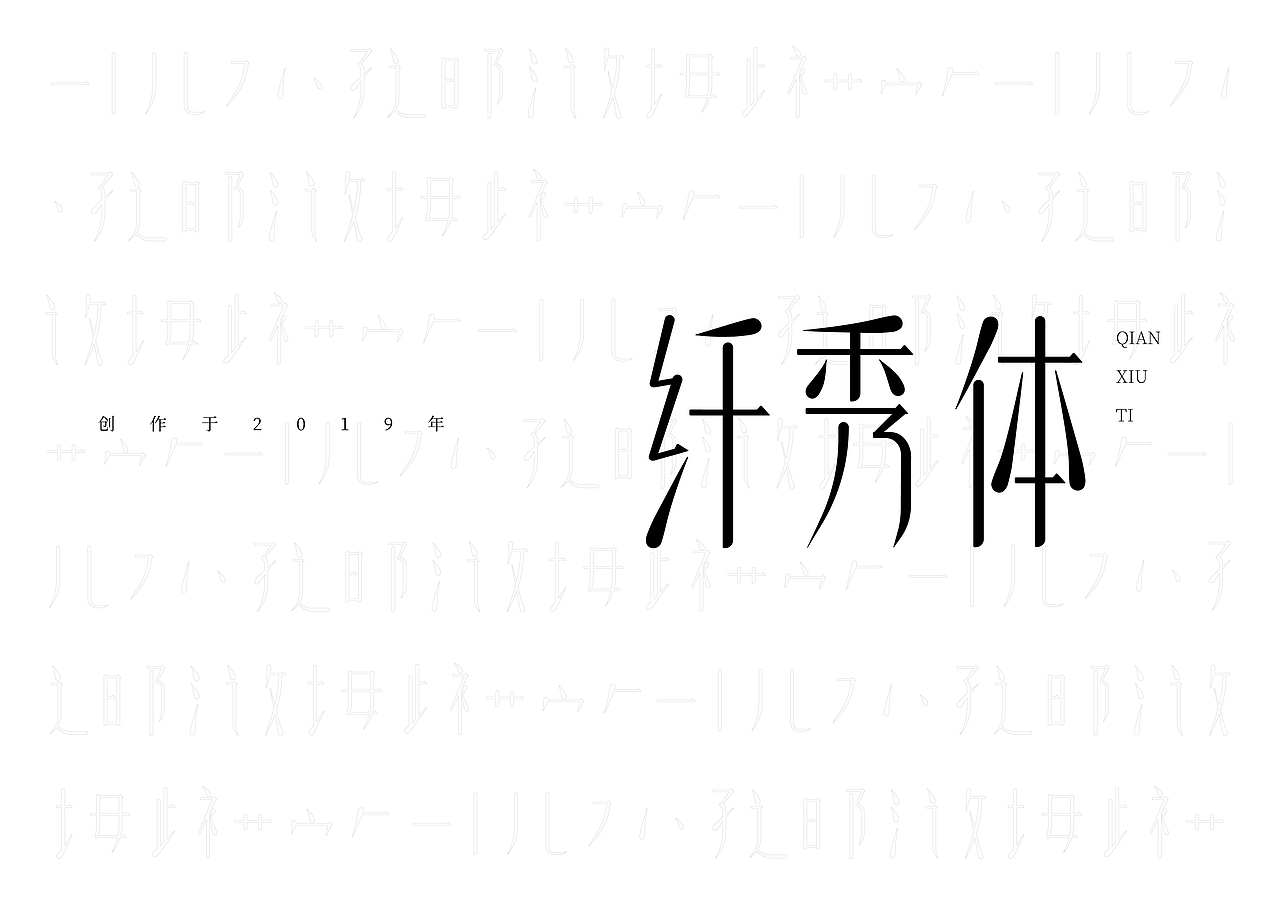
纤秀体&正线体
19年年初在网上看到汉仪字体之星设计大赛
在空闲时间做了2款字体参赛
虽然最后只获得了入围奖
但还是想发出来记录一下自己的努力
纤秀体灵感来源于柳叶,以宋体为基础进行设计。字体保留了宋体的特征,同时也增添了柳叶的特点, 使整款字体更加秀丽、清新。
正线体以黑体为原型,提炼出简洁的线条,使文字整体简约美感。